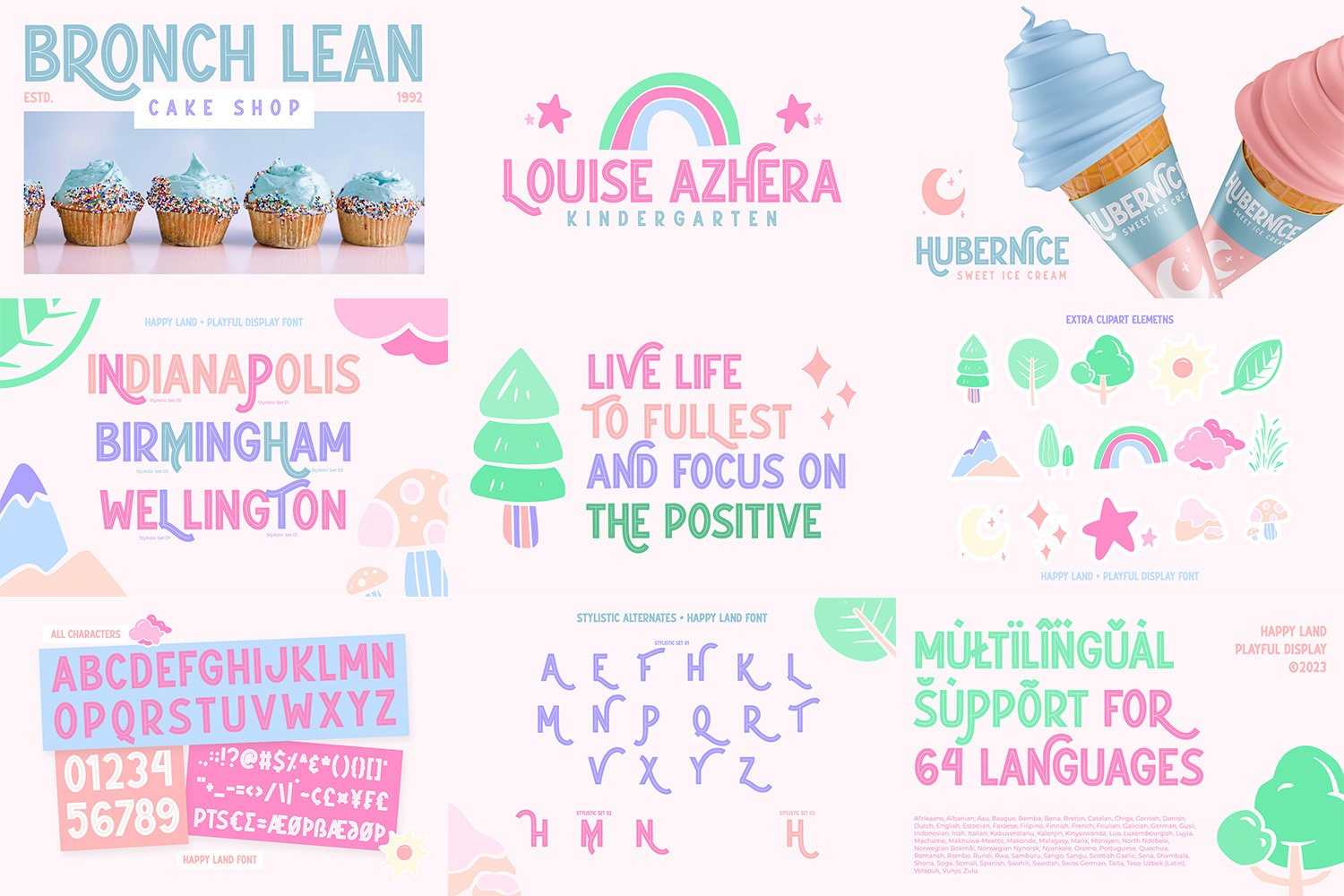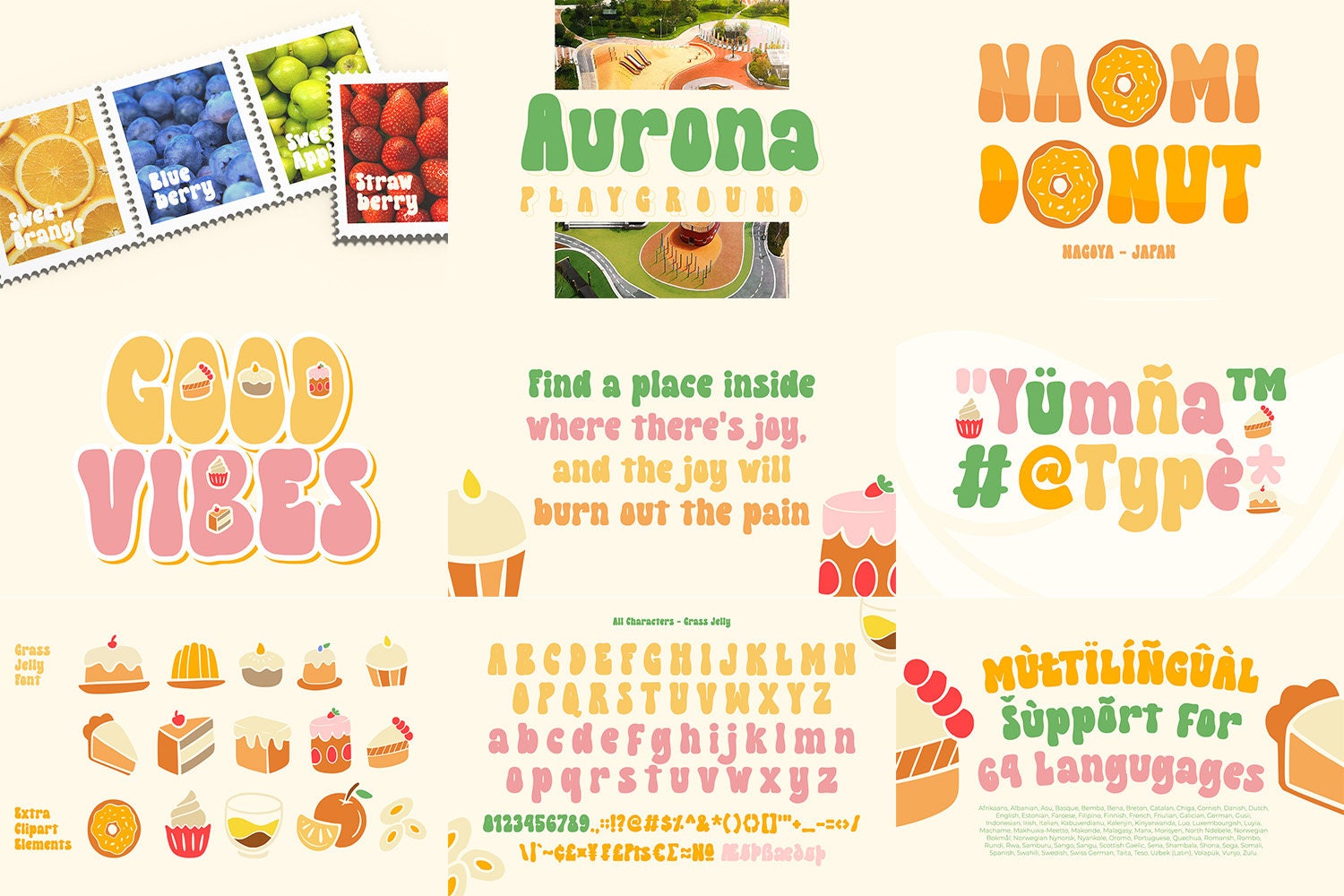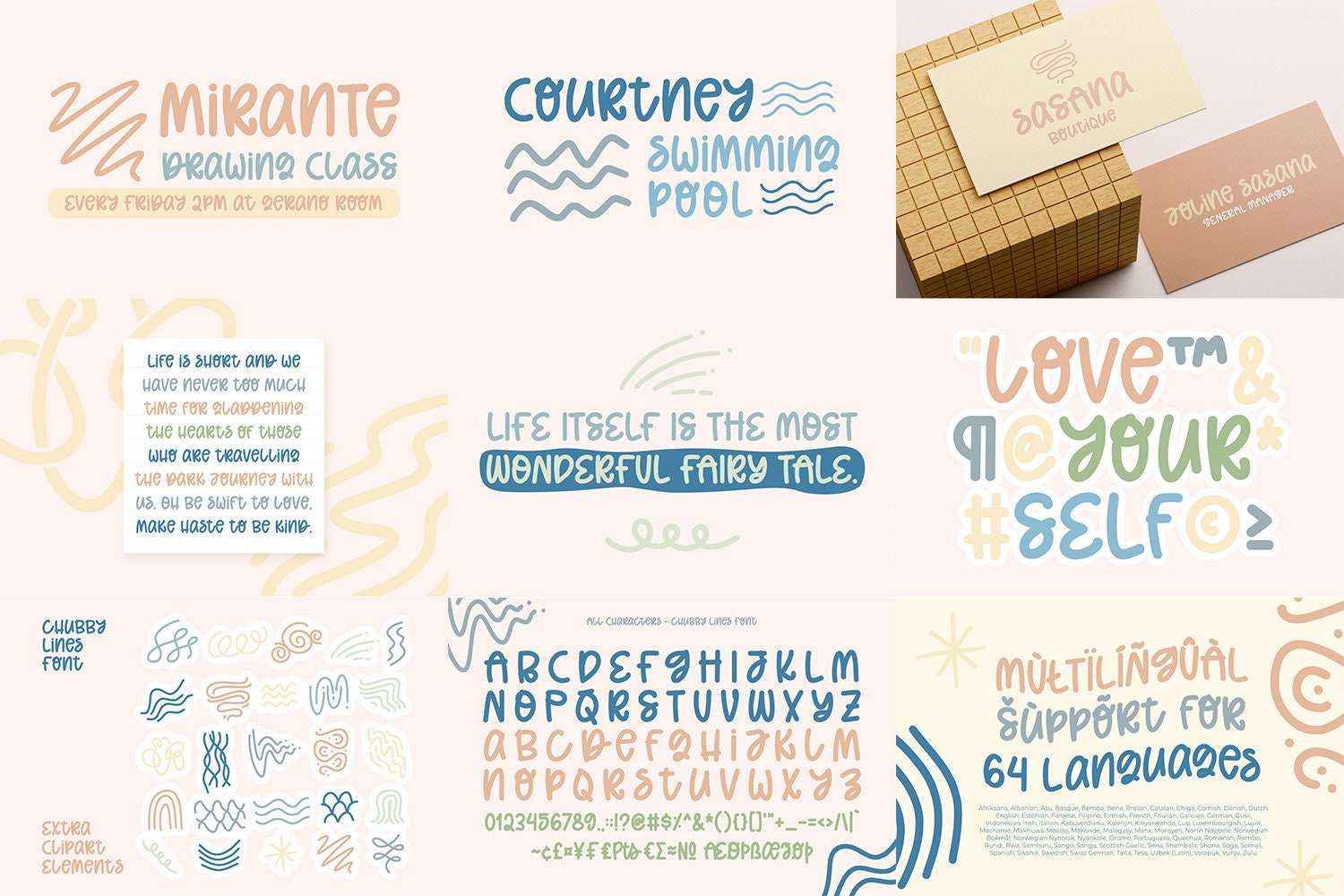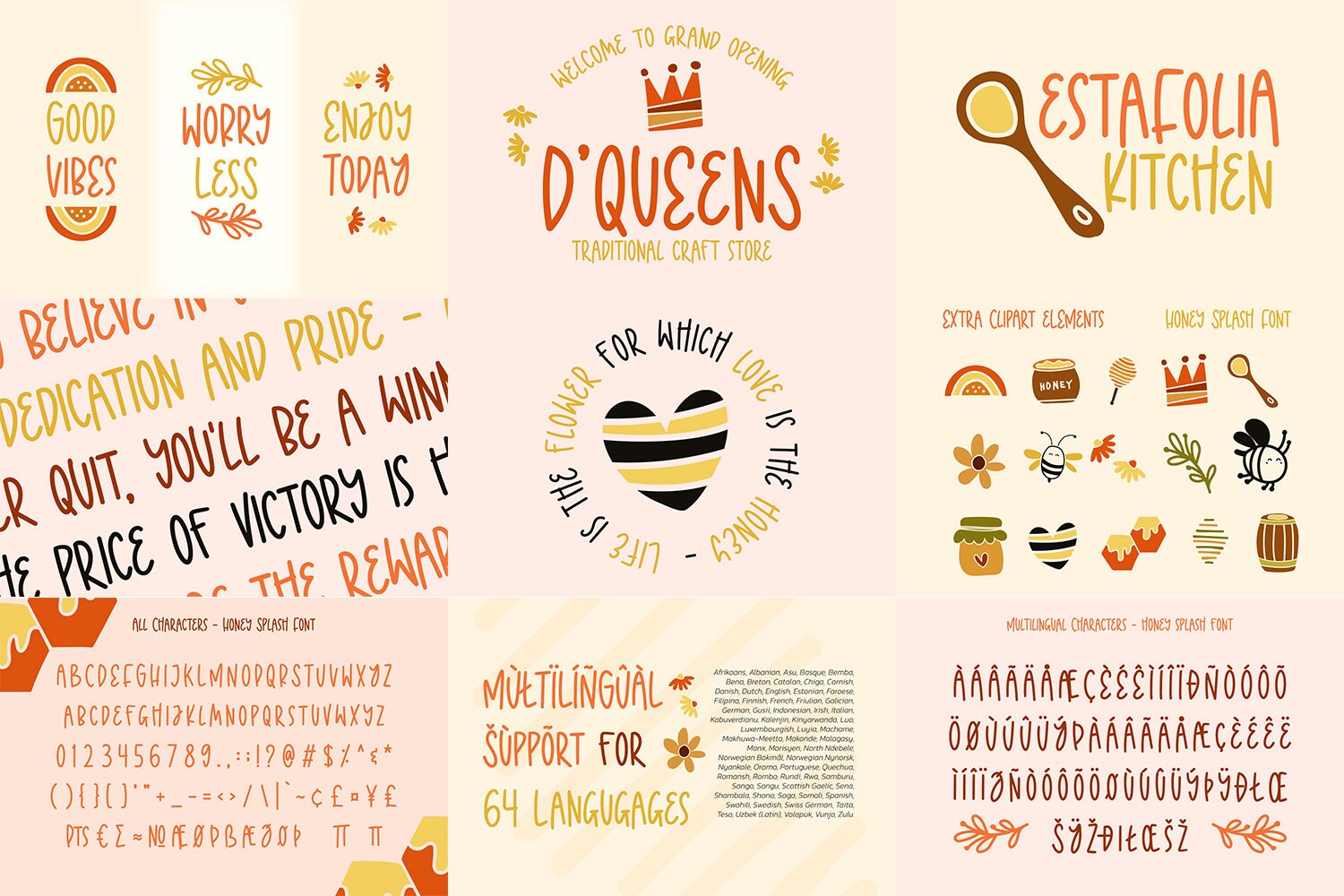
Adorable Font Bundle Vol. 3 – 10 fuentes vintage modernas SVG | Descarga instantánea para Cricut, Canva, Procreate
Eleva tus diseños con Adorable Font Bundle Vol. 3: una colección irresistible de 10 fuentes vintage modernas creadas para aportar encanto, personalidad y un acabado profesional a cada proyecto. Ya seas crafter, diseñador, dueño de un pequeño negocio o estés creando tu primer logo, este pack versátil ofrece resultados premium sin el precio premium. Perfecto para Cricut, Canva, Procreate, apps de Adobe y más; cada fuente es fácil de usar y está lista justo después de la descarga.
Dentro encontrarás una mezcla juguetona y refinada —desde audaz y bubbly hasta dulce y estilo script— ideal para branding, merchandising, publicaciones en redes, empaques, pósters, portadas de libros, citas, invitaciones y gráficos web. El bundle incluye: Honey Splash, Sunday Flicker, Funny Hippo, Pinky Stone, Salty Milky, White Bird, Grass Jelly, Happy Land, Strawberry Junkies y Chubby Lines. Con uso comercial incluido para la mayoría de proyectos pequeños, este bundle es tu kit esencial para una tipografía llamativa en formatos impresos y digitales.
- 10 fuentes premium con estética coherente para combinaciones infinitas
Crea diseños alegres, modernos y únicos — Adorable Font Bundle Vol. 3 lo hace sencillo.